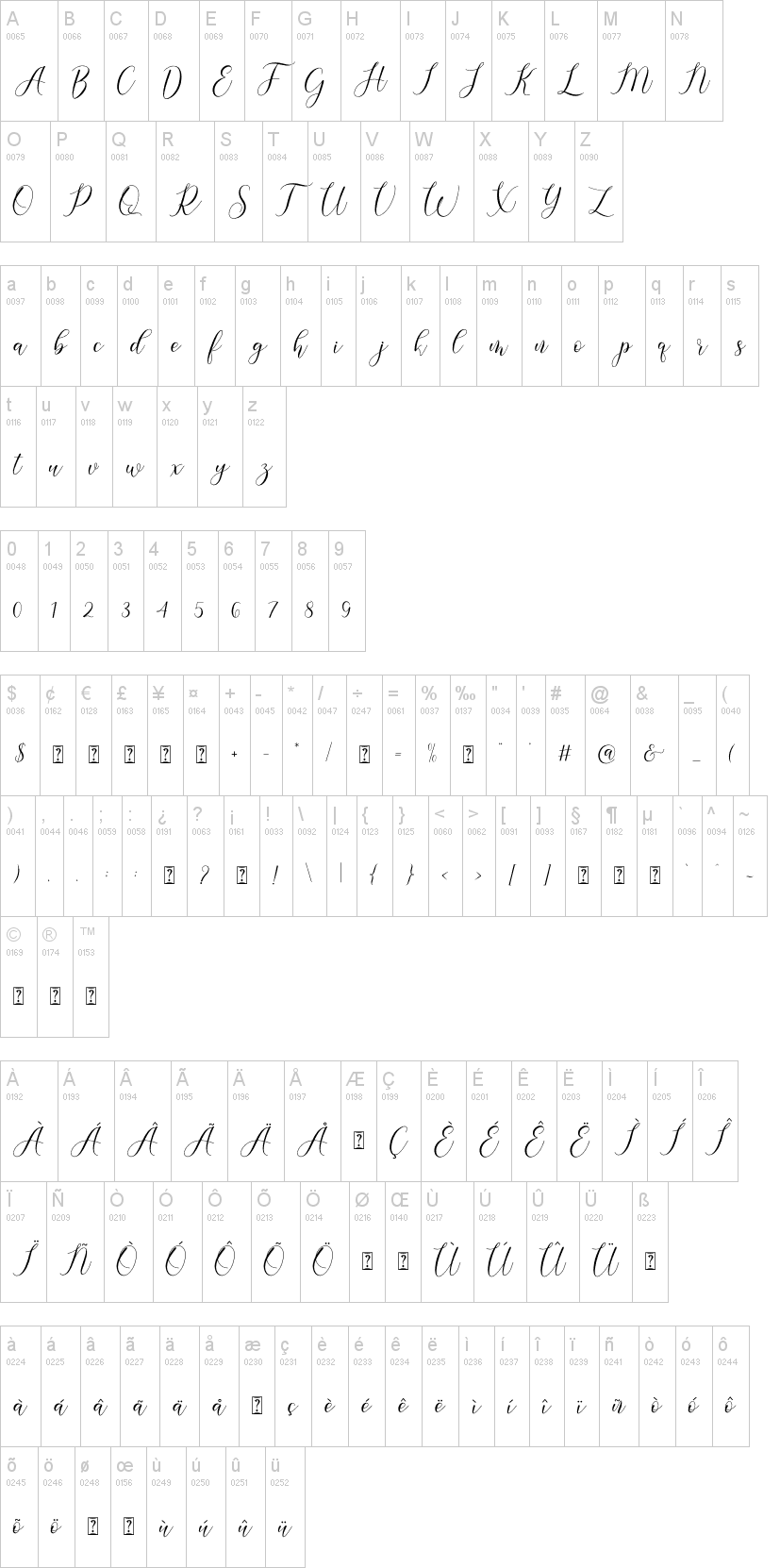
Gresya是一种现代、精美的手写字体,由设计师 Gatis Vilaks 设计。它采用了手写字体的元素,但加入了更多的现代感和设计感,使它在数字、印刷和网页设计中都非常受欢迎。 Gresya 字体非常适合用于品牌标识、海报、手册、传单、包装设计和其他需要具有现代感和个性化的设计项目。它的字母形状非常流畅,同时还添加了一些装饰性的元素,使它的字体更加生动有趣,增加了设计的趣味性。 总的来说,Gresya 字体是一种高效、优美、现代的字体,适用于各种设计项目,为设计师提供了一种非常实用的工具。内容介绍
Gresya是一款非常不错的手写艺术字体,具有很好的视觉感,适合于文化类的宣传设计、商业类品牌的广告和产品包装设计以及个性化文字排版等较多场景。